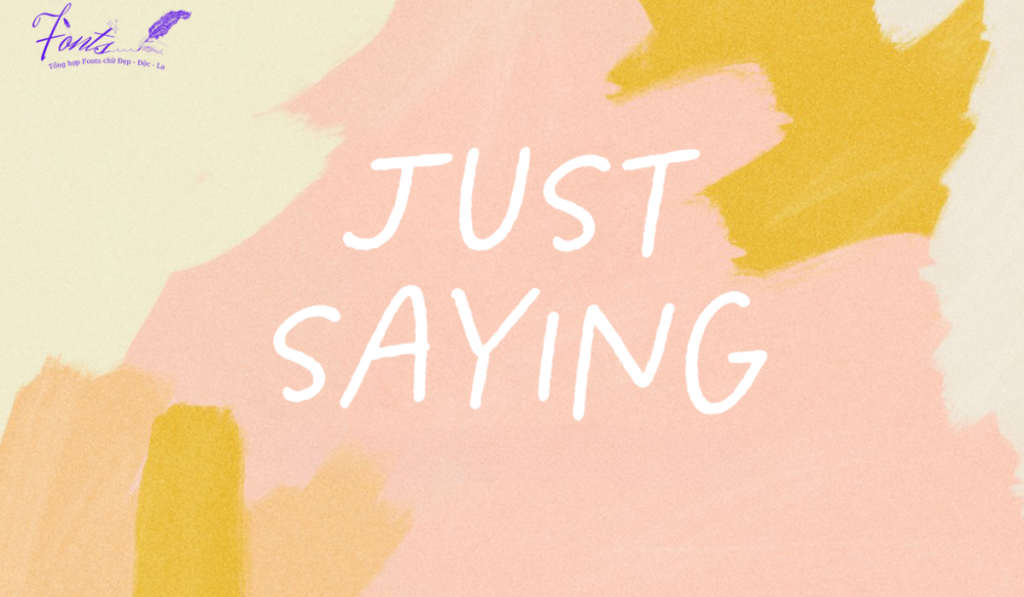
Font SVN Just Saying
Tác giả: Nicky Laatz
Bộ Font: SVN
Phân loại: Độc đáo, vui vẻ
Kiểu chữ: Sans-serif
Độ dày: Regular, Bold
Font SVN Just Saying thuộc bộ font SVN, là kiểu chữ không chân, viết tay, mang phong cách nhẹ nhàng và nghộ nghĩnh.